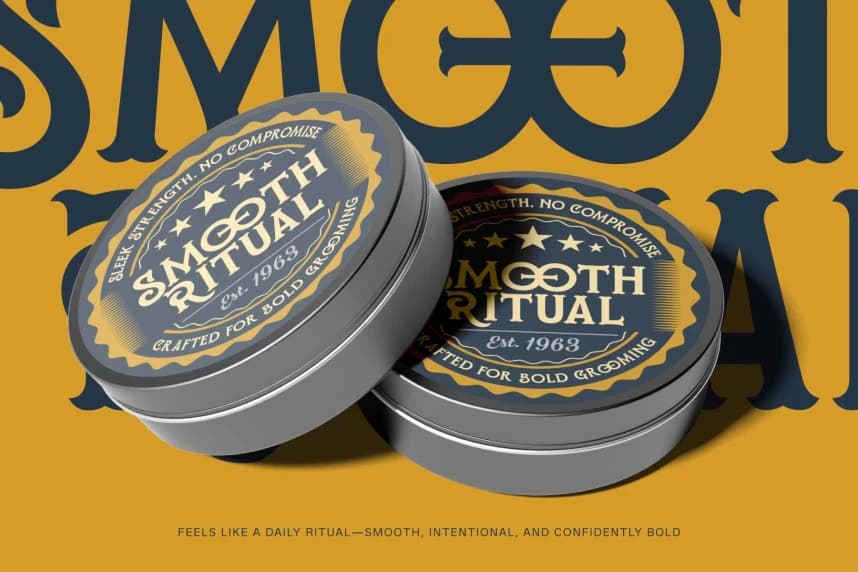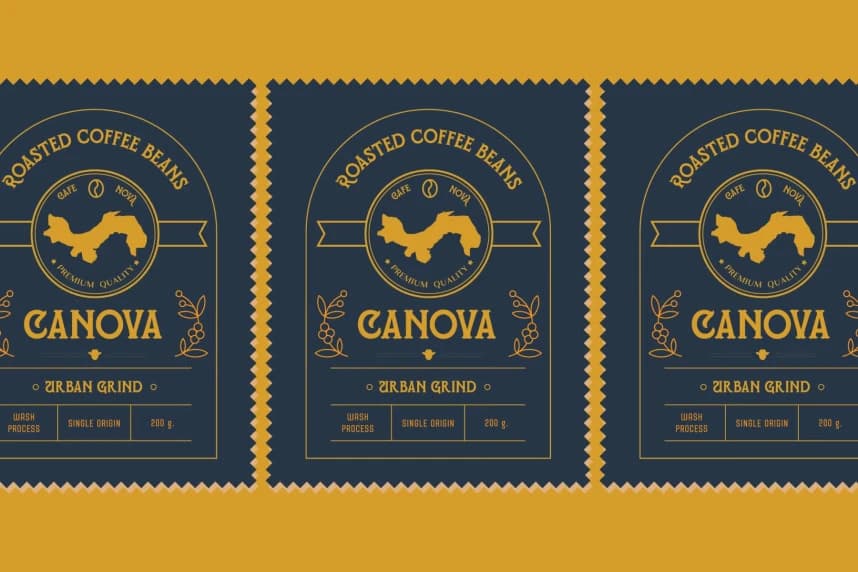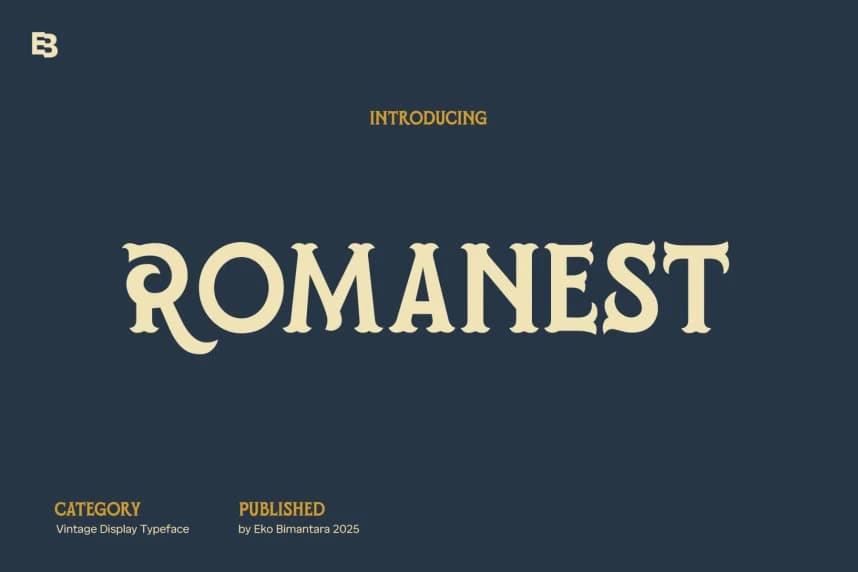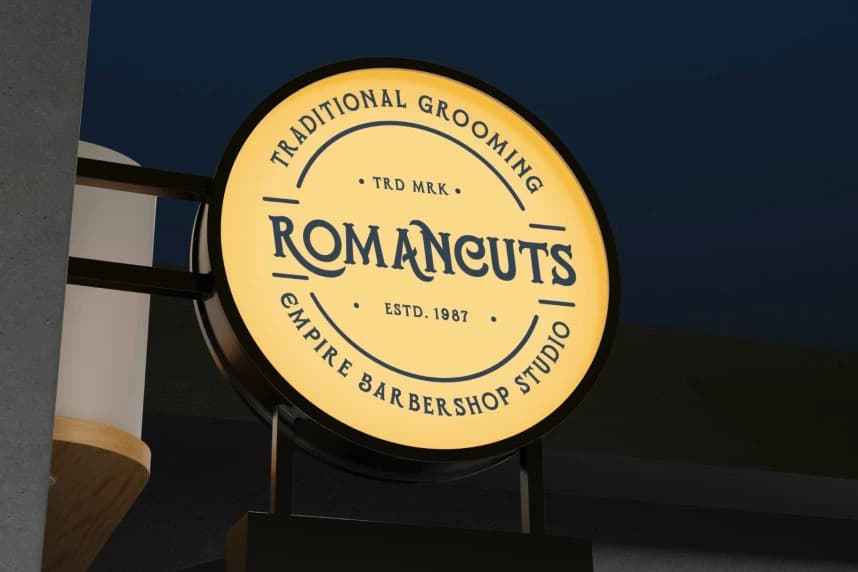
Romanest Font, modern tasarıma cesur vintage karakter kazandırmak için tasarlanmış dekoratif bir serif başlık yazı tipidir. Süslemeli ayrıntılar ve ifadisel eğrilerle zenginleştirilmiş olan bu yazı tipi, her karakterin kasıtlı ve el yapımı hissi vermesini sağlar.
Romanest Font, modern tasarıma cesur bir vintage karakter katan süslemeli bir serif gösterim yazı tipidir. Süs öğeler ve ifade dolu eğrilerle zenginleştirilmiş olan bu tasarım, her karakterin kasıtlı ve el yapımı hissini verir.